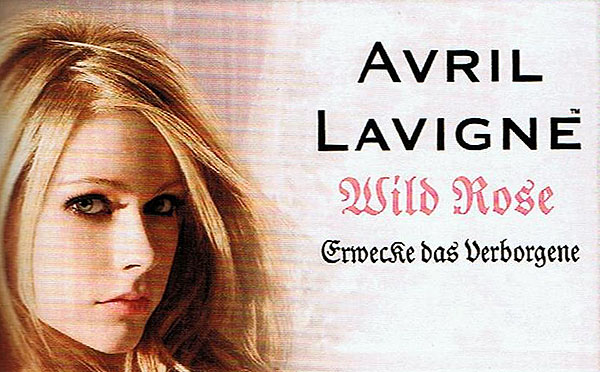
Ich finde aber die Unterlänge viel zu kurz, daher könnte es ein Versal-ß hätte werden sollen.
Auf größeren Abbildungen des Umschlags kommt es mir so vor, als ob der vertikale Strich beim ß gegenüber dem R und dem U dicker wäre, deshalb bleibe ich bei der Vermutung, dieser Buchstabe wurde einfach größer gesetzt (und dann vertikal zentriert).
Das scheint mir auch so, ich finde trotzdem die Unterlänge etwas arg kurz geraten.
Weiß denn jemand aus welcher Schrift der Titel gesetzt ist?
… unpassendes Minuskel-Eszett …
Ist die Unterlänge dazugebastelt oder gibt es das in dieser Form?
Ich glaube das ist absichtlich verzerrt, damit es mehr nach verknittertem Papier aussieht, und nicht, um aus dem kleinen ein großes ß zu bilden.
ich habe gerade in einer Zeitschrift meiner Freundin das Verborgene erweckt … äh … entdeckt:
Ein Majuskel-K und ein fremdes V – wieso macht man so etwas? :shock:
Interessanterweise spuckt mir Google nach kurzer Befragung noch eine andere Version dieser Werbeanzeige aus, in der zwar nicht die obligatorische ck-Ligatur, aber zumindest die korrekten Frakturbuchstaben auftauchen. Das bedeutet, den Zeitschriftenmachern waren wohl einfach das Fraktur-k und das V zu »unleserlich«. :-o
Verrückte Welt. :neenee:
Normalerweise legen die Anzeigenabteilungen von Zeitschriften nicht selber Hand an eine solche Anzeige (Es sei denn, es handelt sich um ein sogenanntes Advertorial, Dein Beispiel ist aber keins.), sondern sie bekommen fix und fertige Druckunterlagen angeliefert, meist Druck-PDFs. Der Grund für die eigenwilligen Schriftenabweichungen müssten bei der Agentur liegen, die diese Anzeigen erstellt hat.
Das bedeutet, den Zeitschriftenmachern waren wohl einfach das Fraktur-k und das V zu »unleserlich«. :-o
Für die Zielgruppe sind die Buchstaben ›V‹ und ›k‹ der Original-Fraktur vermutlich nicht als solche erkennbar. Nichts anderes wird der Grund für diese Verschlimmbesserung sein.
Wenn V und k nicht lesbar waren, könnte man drüber diskutieren, ob das jetzt eine "Verschlimmbesserung" oder doch eine Verbesserung ist (im Kontext, dass das alles Verkaufsförderung, nicht Kulturpflege ist).
Wär das "K" nicht zu groß/breit, wäre es mir ehrlich gesagt nicht negativ aufgefallen.
Das "s" in "Rose" ist übrigens auch noch "falsch".
Normalerweise legen die Anzeigenabteilungen von Zeitschriften nicht selber Hand an eine solche Anzeige […] Der Grund für die eigenwilligen Schriftenabweichungen müssten bei der Agentur liegen, die diese Anzeigen erstellt hat.
Das dachte ich auch, aber ich fand im Netz sowohl die oben verlinkte »richtigere« Version als auch eine komplett baugleiche, englisch beschriftete Version, so dass sich mir der Verdacht aufdrängte, dass die Agentur ursprünglich ganz annehmbare Beschriftungen angefertigt hatte, die dann aber in irgendeiner späteren Stufe »verbessert« wurden (weil man beim Leser keine Frakturlesekompetenzen voraussetzen konnte/wollte?).
Ansonsten hat Sebastian natürlich recht: Für die Zielgruppe bilden die Veränderungen sogar mit Sicherheit eine »Lesehilfe«. Andererseits frage ich mich dann, wieso man sich überhaupt für eine solche Schrift entscheidet, wenn man sie dann im Einsatz so verbiegen muss. :-?
P. S.: Selbst als »lang-s-Verfechter« finde ich das rosafarbene »White Rose« hier irgendwie stimmiger als »White Roſe«. :-)
Wenn V und k nicht lesbar waren, könnte man drüber diskutieren, ob das jetzt eine "Verschlimmbesserung" oder doch eine Verbesserung ist (im Kontext, dass das alles Verkaufsförderung, nicht Kulturpflege ist).
Darüber brauchen wir, glaube ich, gar nicht diskutieren. Es stellt mit großer Sicherheit ein Zugeständnis an die Lesegewohnheiten der Zielgruppe dar.
In der Luthersche Fraktur™ von Linotype sind die typischen Fraktur-k und -x nicht mehr enthalten. Noch nicht mal als Alternativ-Buchstaben.
Hier ein Scan der Lutherschen Fraktur der D. Stempel AG, Frankfurt am Main (aus Albert Kapr »Fraktur«):
Und hier die gleiche Zusammenstellung gesetzt aus der Lutherschen Fraktur LT Pro:
In der Lutherschen Fraktur von Elsner + Flake, Scangraphic und Typoart sind k und x übrigens in der ursprünglichen Form enthalten. […] Ich kann ja verstehen, dass Linotype mit Blick auf den außerdeutschen Markt eine moderne k- und x-Form anbietet. Was ich jedoch überhaupt nicht verstehe, dass die historisch korrekte Form nicht wenigstens als Alternative im Font enthalten ist.
(Das Aussterben des frakturtypischen k hatte ich in der Fraktur-Gruppe bereits beklagt. Da ich nicht weiß, ob man den Beitrag lesen kann, ohne Fraktur-Gruppenmitglied zu sein, habe ich hier meinen Text und die Bilder nochmals wiedergegeben.)
Zumal sich die Buchstaben ja aus dem Kontext ergeben.
Da steckt die selbe respektlose Denkart dahinter, die dazu führt, daß hiesige Gestalter fremde Alphabete wild verwursten um einen irgendwie exotischen Eindruck zu erwecken. Da wird eben mal ein kyrillisches Д (D) zum A umfunktioniert oder ein hebräisches ש (S) zum W. Für die Kanadier ist eine deutsche Schrift dann eben auch nur ein Steinbruch, aus dem man sich nach Belieben herausbricht, was gefällt — das ist die Disneysierung der Typographie.